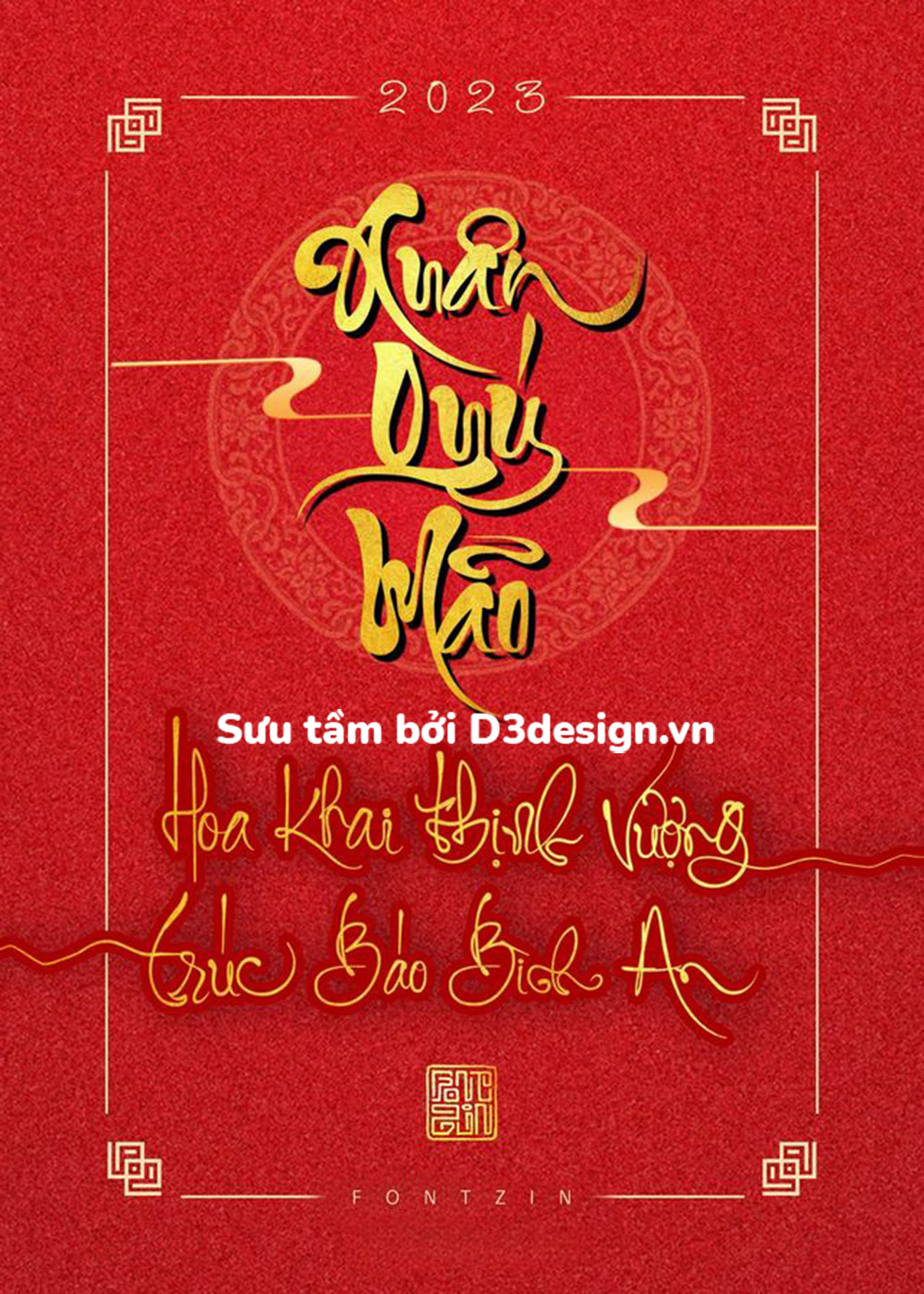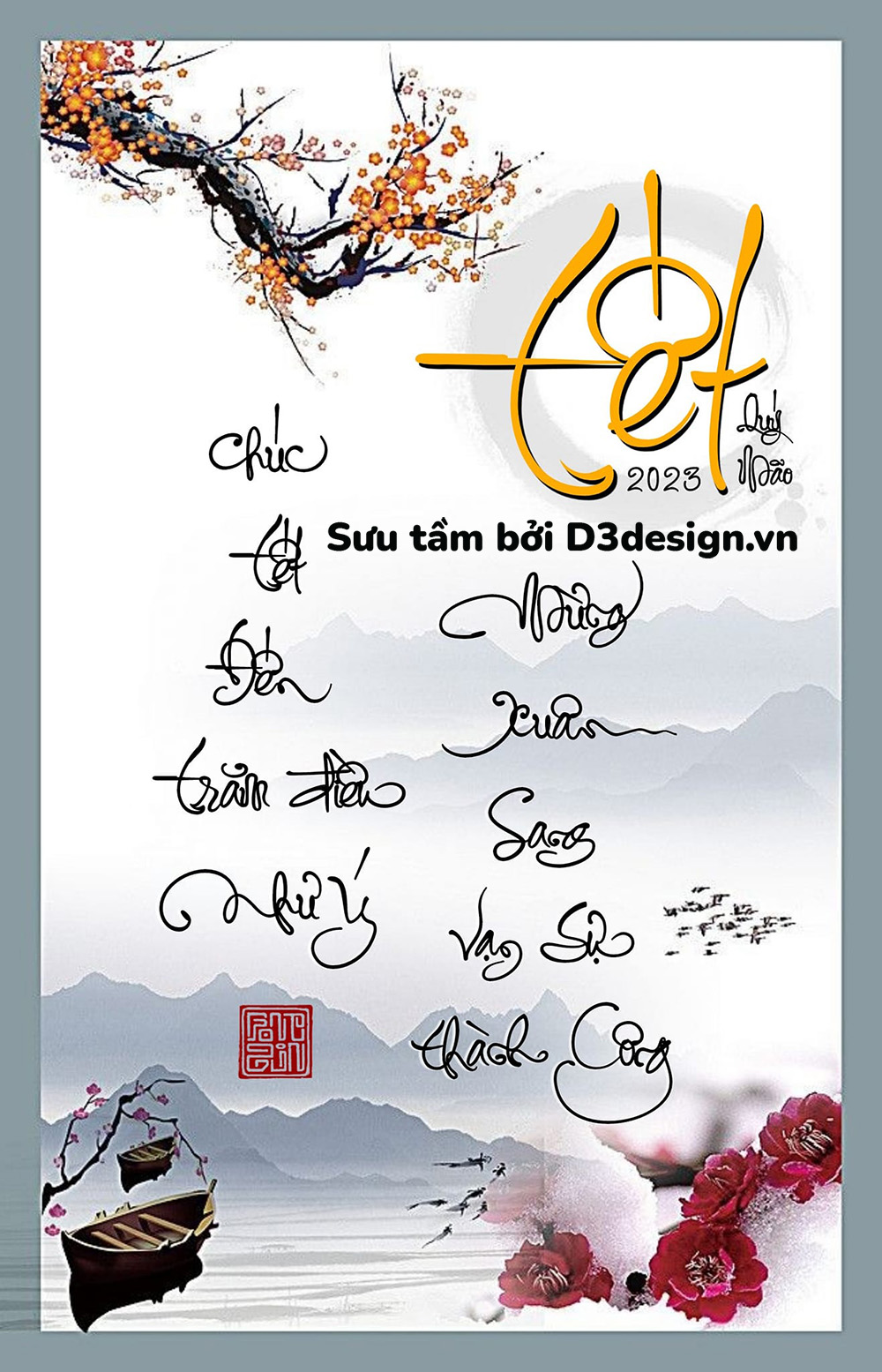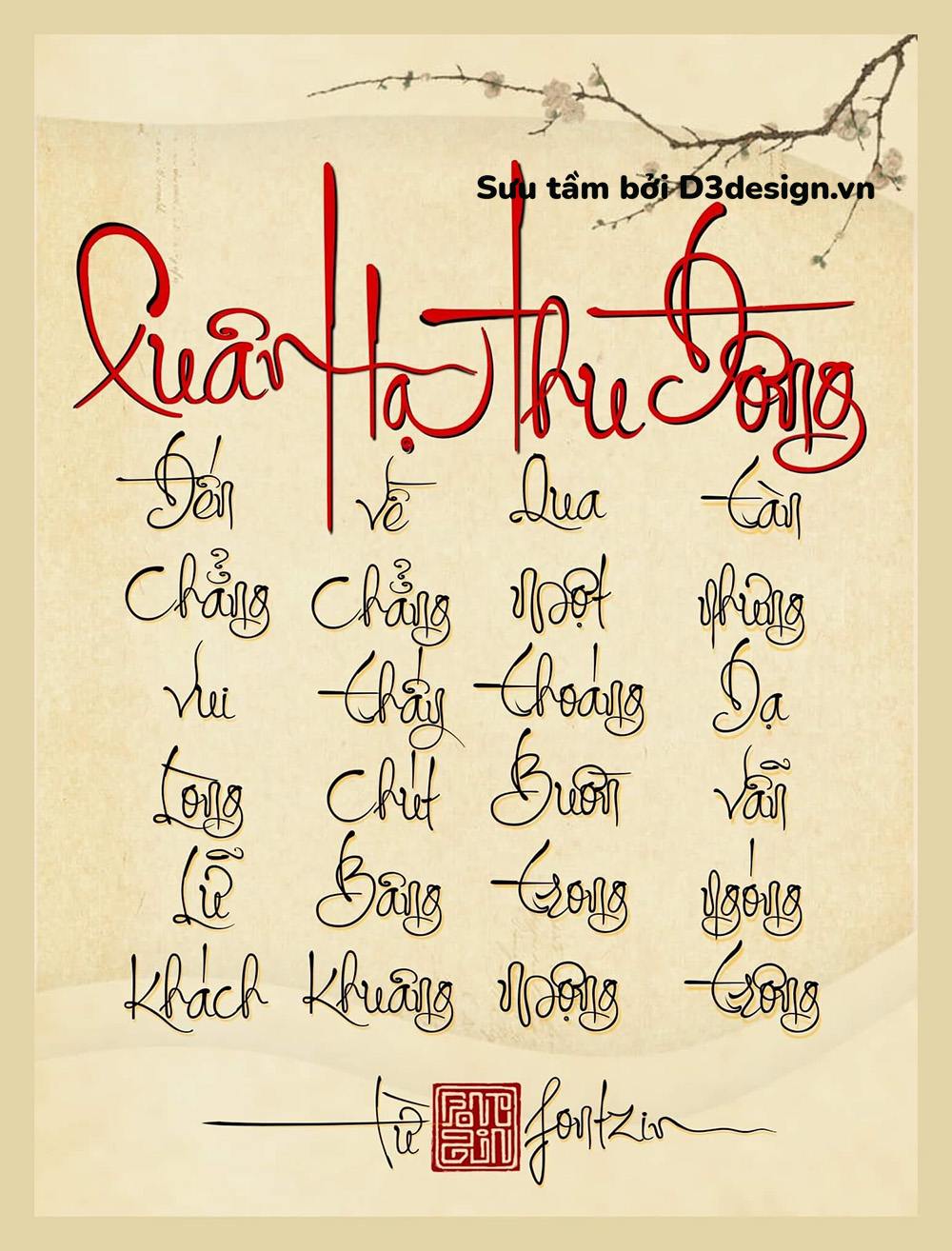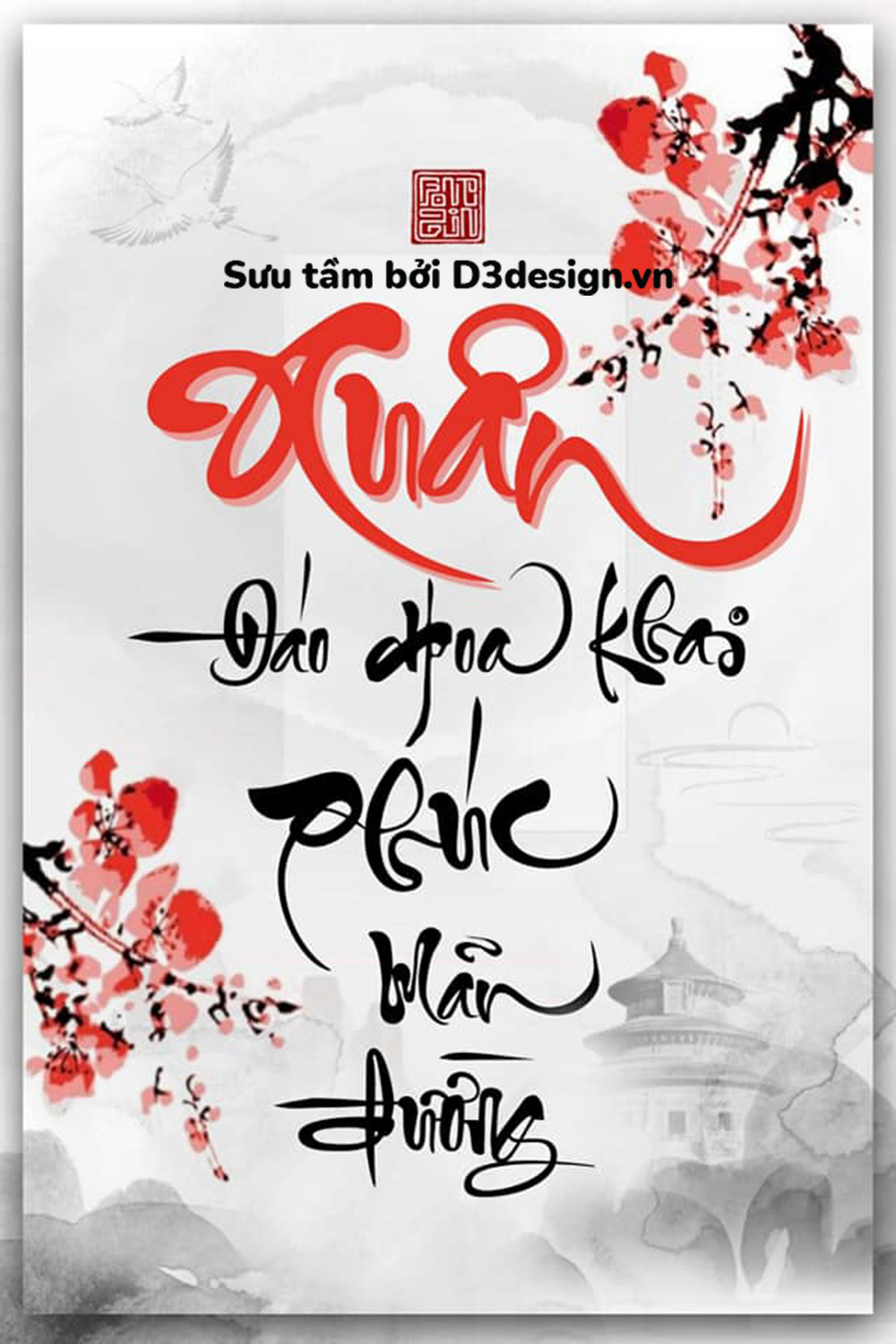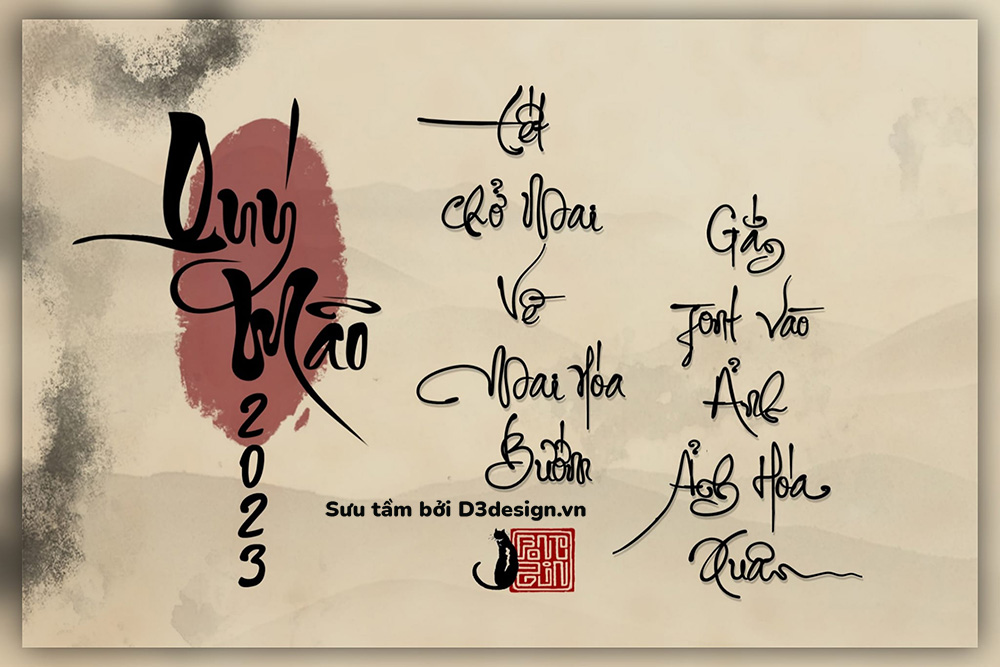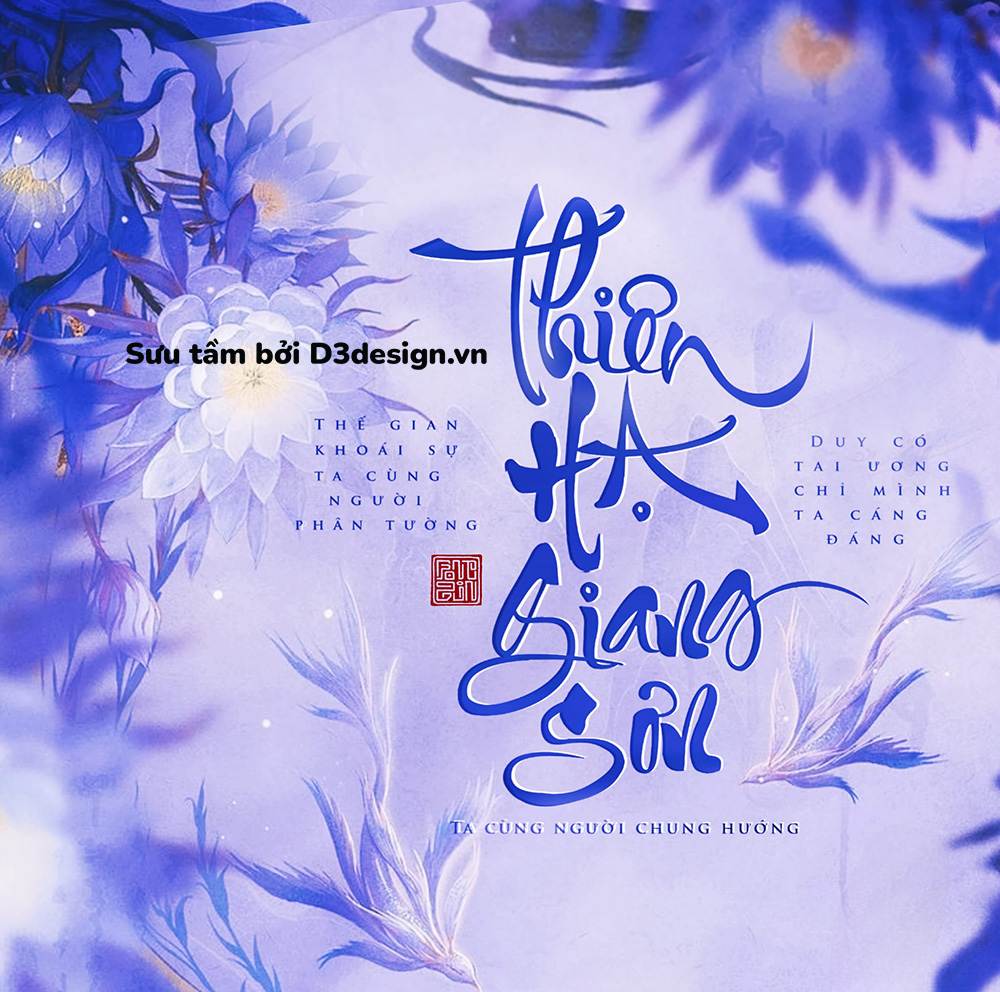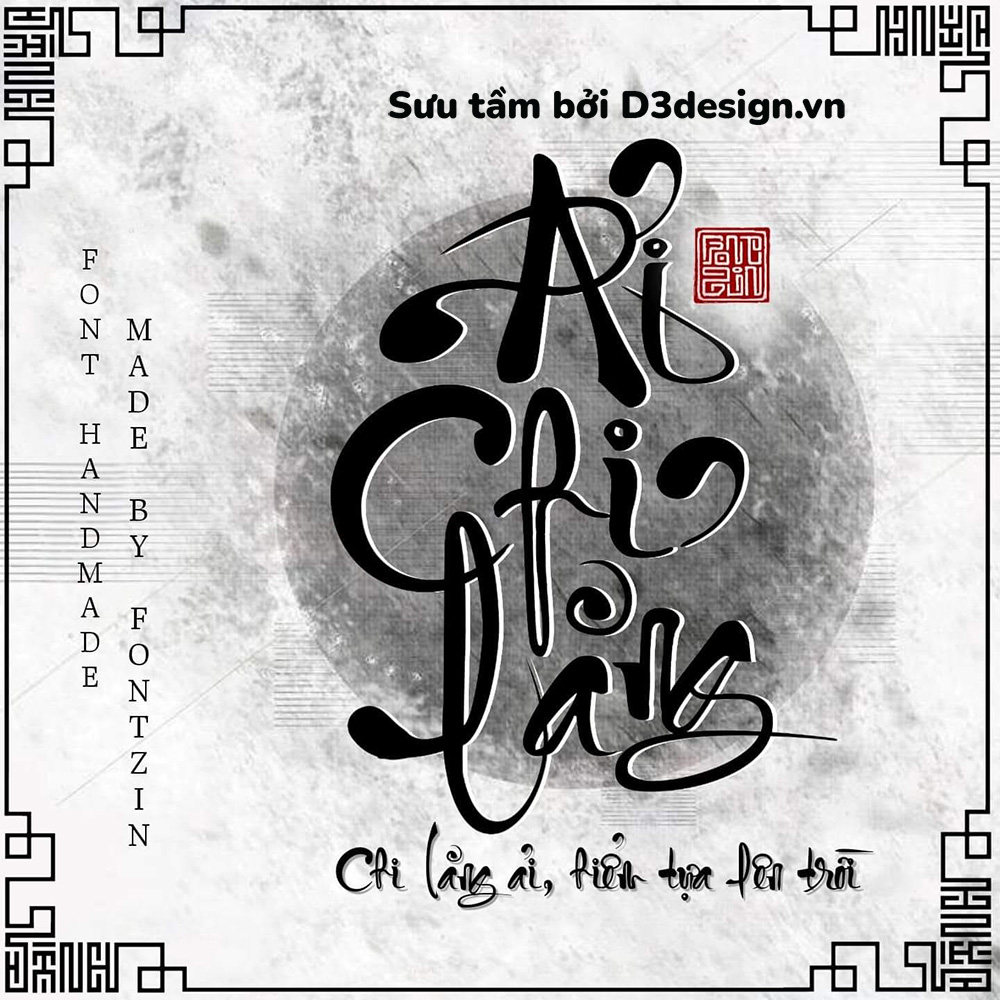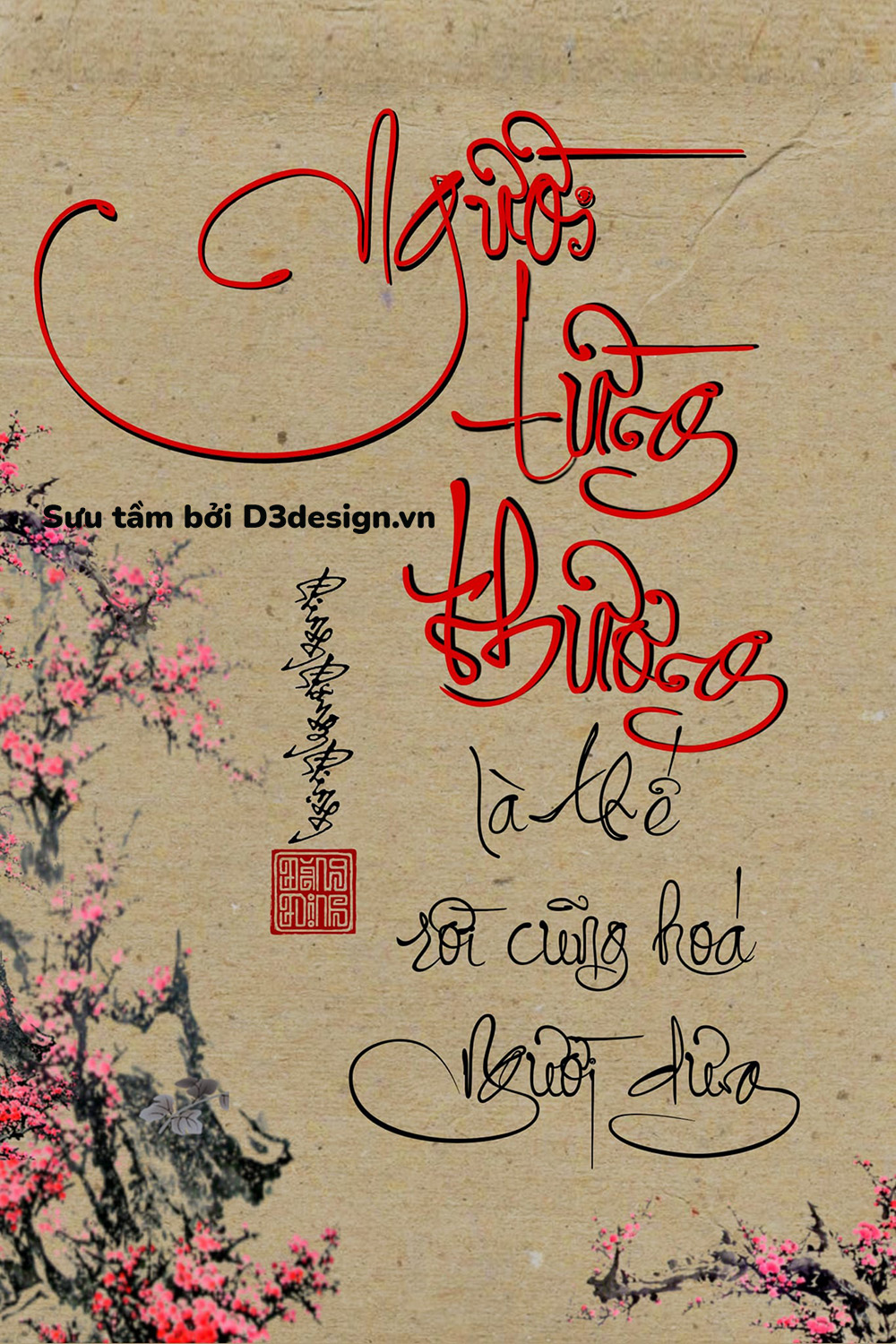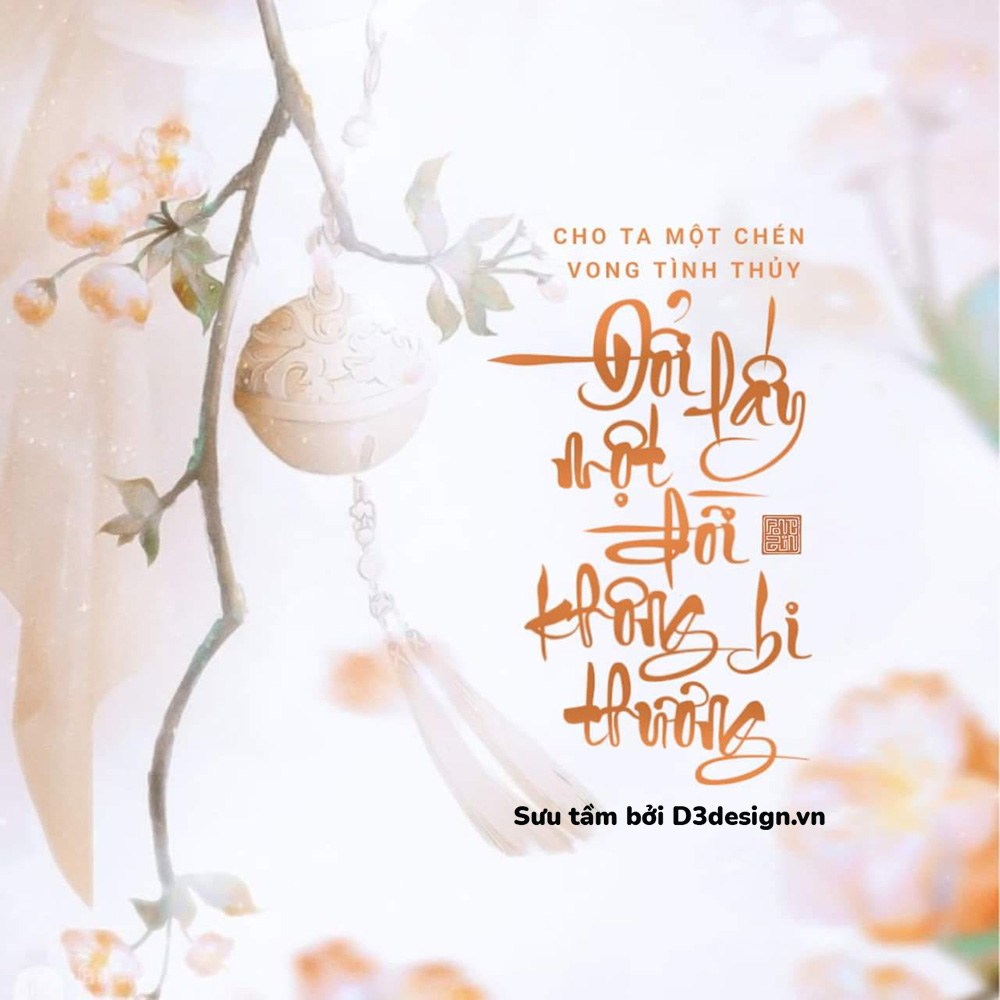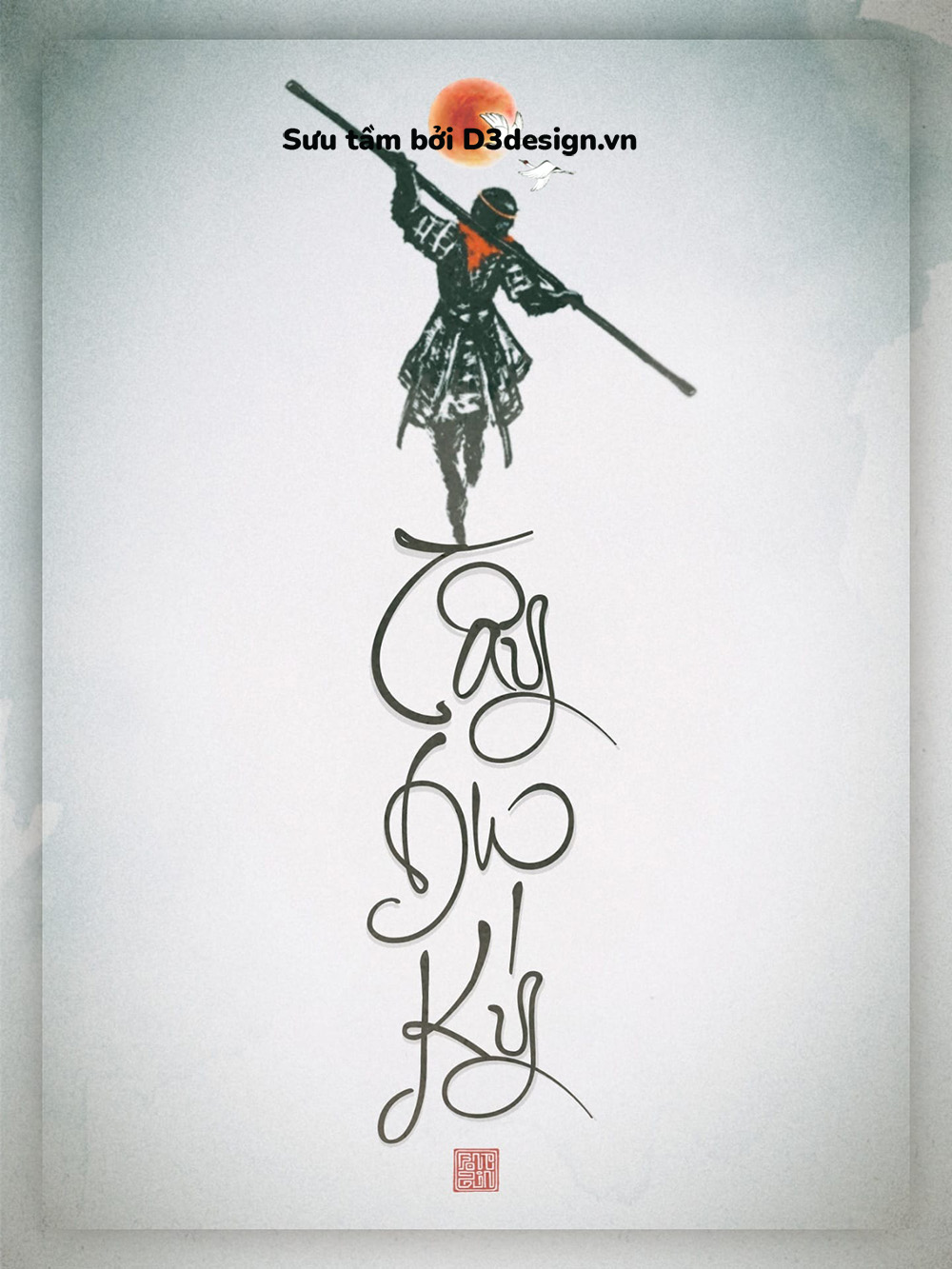
Tải 2 Font Thư Pháp Việt Hóa Cực Đẹp Dành Cho Tết Quý Mão 2023
Font chữ thư pháp hay còn được gọi là font chữ ông đồ, các nét chữ đặc biệt, phá cách, uốn lượng chứ không gọn gàng và đơn giản như các font chữ thông thường. Font chữ thư pháp thường được tạo nên từ những tác phẩm nghệ thuật đẹp mắt. Team Fontzin đã làm 2 font thư pháp thiết kế bản full glyph.